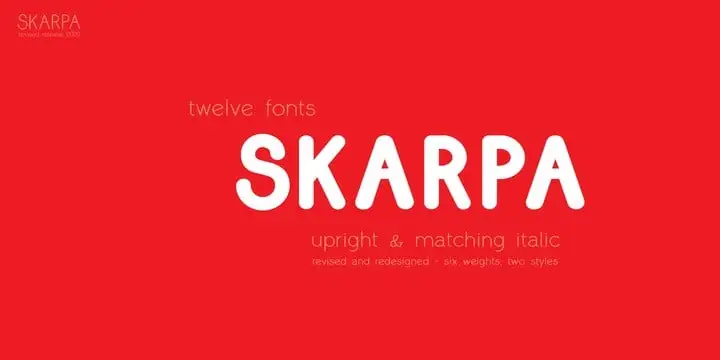
Introduzimos a Skarpa Sans Serif Font, uma elegante tipografia com traços marcantes e robusta, especialmente projetada para usos fortes, mas que também possui uma pegada versátil. Esta nova revisão incluiu um novo olhar sobre as formas de letras, assim como ajustes em kerning e métricas dos arquivos. Com seu design imponente e moderno, a Skarpa Sans Serif Font é ideal para ambientes que valorizam estilo, força e facilidade de leitura. Não importa se você está criando materiais online ou offline, essa fonte estará à altura de qualquer demanda, desde cartazes gigantes até pequenos títulos em websites.